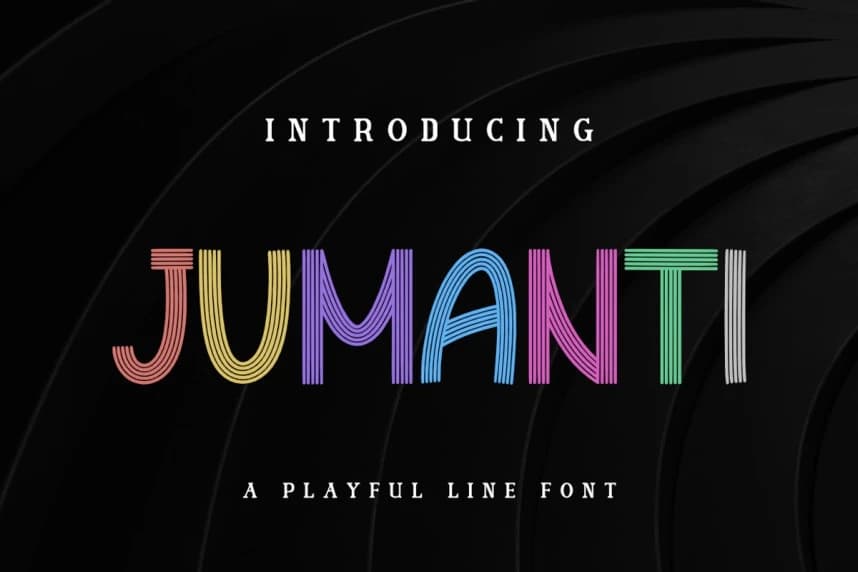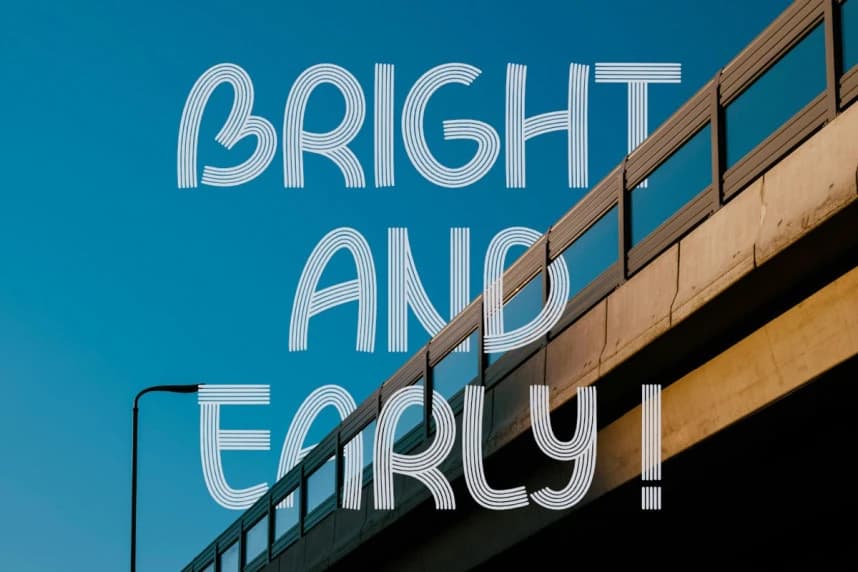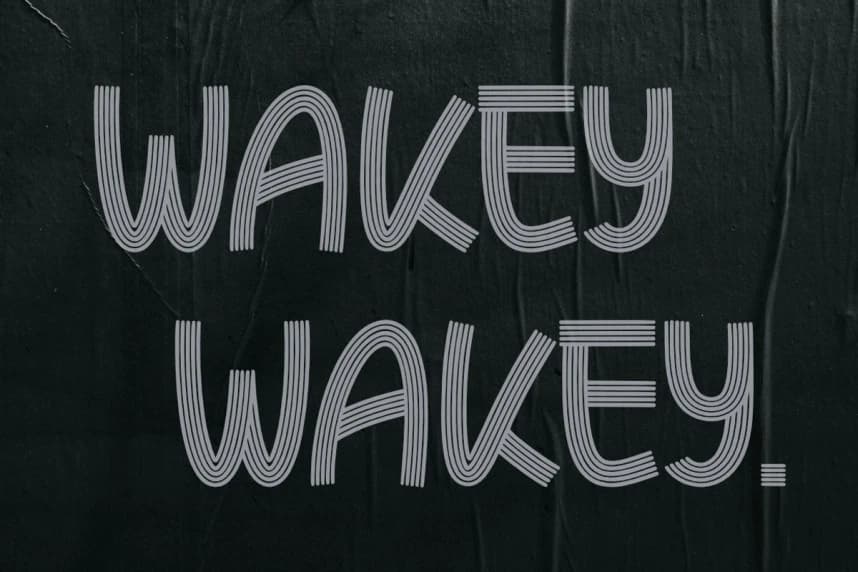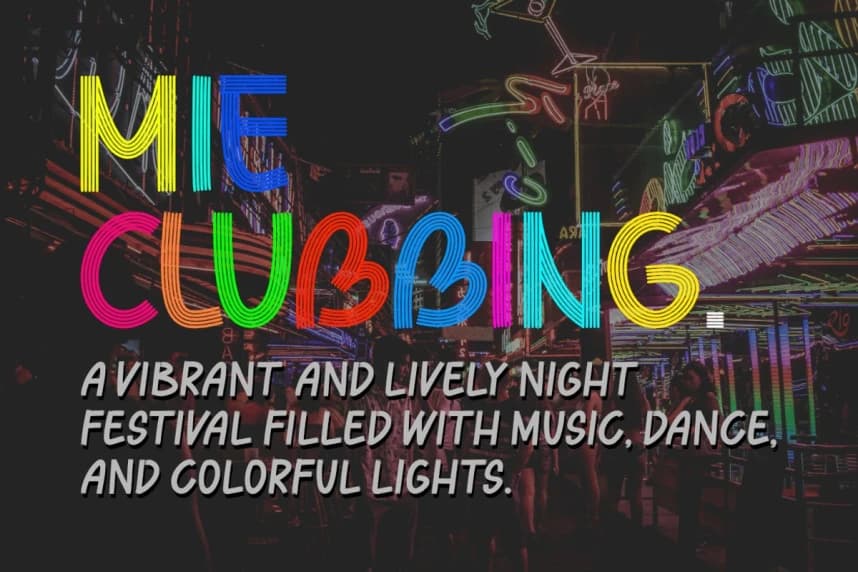
Jumanti Playful Font
Jumanti Playful Font, süsleyici tipografiden ilham alınmıştır. Bu yazı tipi, yüksek bir premium kaliteye sahiptir ve afişler, alıntılar, posterler, pankartlar, ambalajlar, ticari ürünler, logotipler ve çok daha fazlası için kullanılabilir.
Jumanti Playful Font, dekoratif tipografiden ilham alınmıştır. Bu font yüksek kaliteli bir premium seviyesinde üretilmiştir ve broşürler, alıntılar, posterler, pankartlar, ambalajlar, ticari ürünler, logotipler ve çok daha fazlası için kullanılabilir.